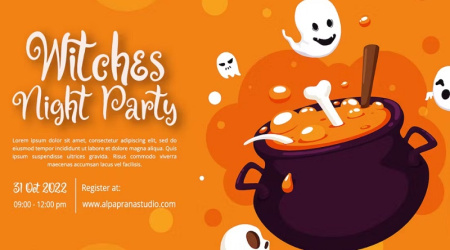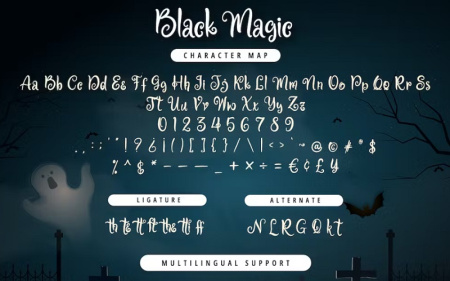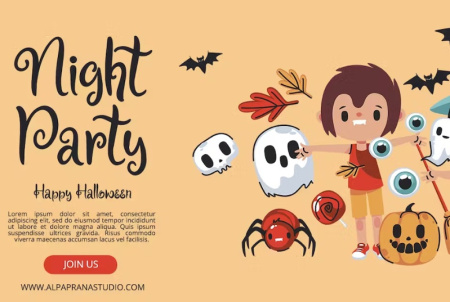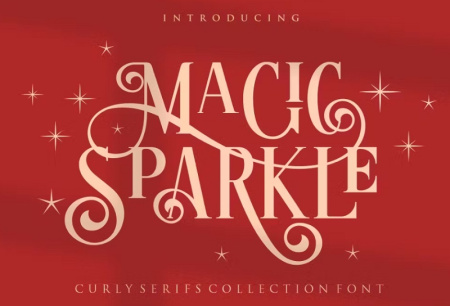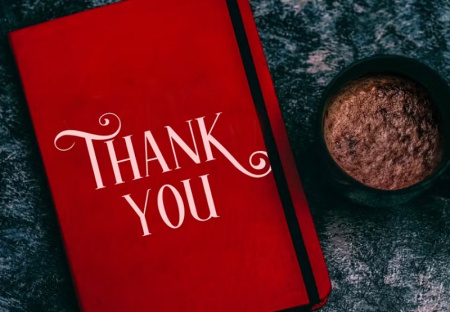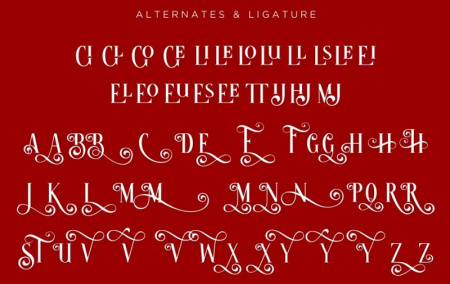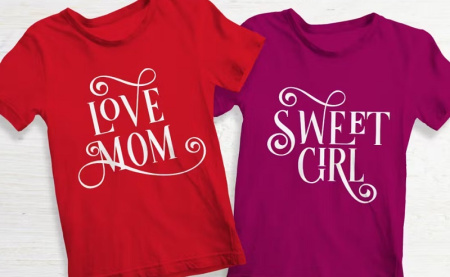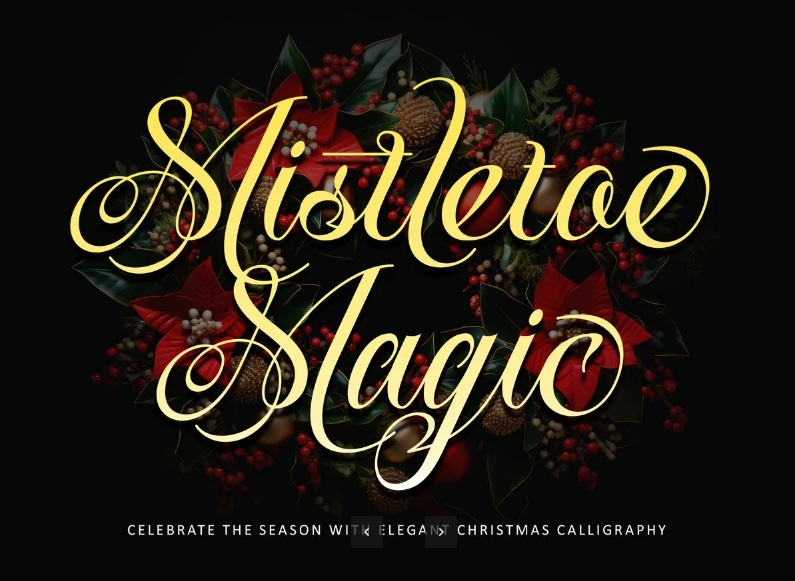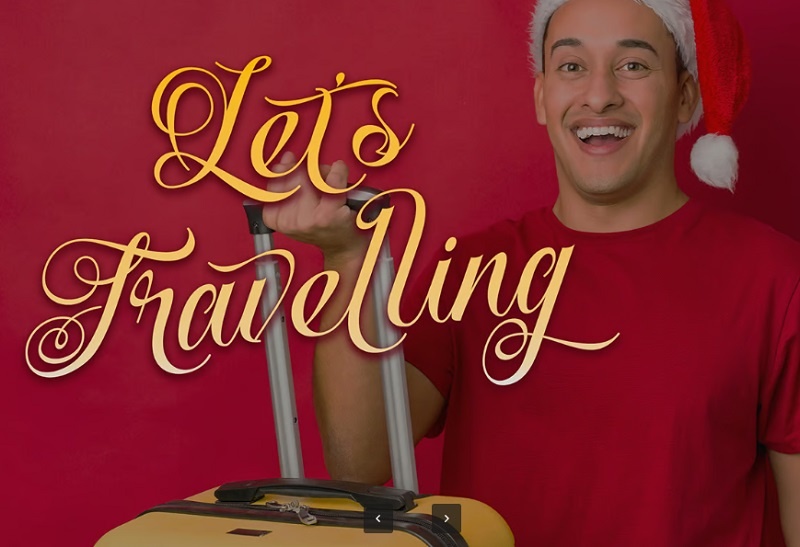
فونت انگلیسی جادویی Black Magic شامل 4 فونت جادویی انگلیسی و نمایشی خیره کننده با حس های زیبا و بازیگوش است. اگر برای طراحی های خود به فونت های جادویی انگلیسی نیاز دارید بدون شک این یکی از فونت های زیبا و کاربردی می باشد. از این فونت انگلیسی برای برندسازی، طراحی های تبلیغاتی، طراحی لوگو و ... می توانید استفاده کنید.
2- فونت انگلیسی مجیک و جادویی Magic Sparkle
فونت بسیار زیبا مجیک و جادویی با کاراکتر های مجعد و ظاهری منحصر به فرد است که برای هر پروژه ای عالی است. این فونت انگلیسی مجیک و جادویی Magic Sparkle با سبکی مدرن و در عین حال لوکس می باشد. مناسب برای صنایع دستی، پوستر، کتاب، برندسازی، نقل قول ها، قالب های چاپی، بسته بندی، دعوت نامه ها، برچسب های موسیقی، برچسب های محصولات، لوگوها و موارد دیگر.
3- فونت انگلیسی به صورت جادویی Mistletoe Magic
در این پست با معرفی فونت انگلیسی به صورت جادویی به سبک خوشنویسی و ظریف با شما همراه هستیم. این فونت انگلیسی جادویی حسی از زرق و برق و لوکس بودن را به طراحی ها می دهد. شامل فایل های TTF، OTF، WOFF، اعداد و علائم نگارشی و حروف کوچک و بزرگ می باشد.
اگر به دنبال یک تایپوگرافی متفاوت برای پروژه های خلاقانه هستید، این فونت انگلیسی جادویی به سبک فانتزی می تواند انتخاب مناسبی باشد. طراحی خاص و حال و هوای خیال انگیز این فونت، برای ساخت عنوان، پوستر، کاور، طراحی شبکه های اجتماعی، کارت دعوت و پروژه های گرافیکی با فضای فانتزی کاربرد دارد. این فونت انگلیسی به صورت جادویی با ظاهر متفاوت خود می تواند به نوشته ها جلوه ای مرموز و جذاب بدهد و برای پروژه هایی با تم جادو، داستان های فانتزی و طراحی های خلاقانه مورد استفاده قرار بگیرد.